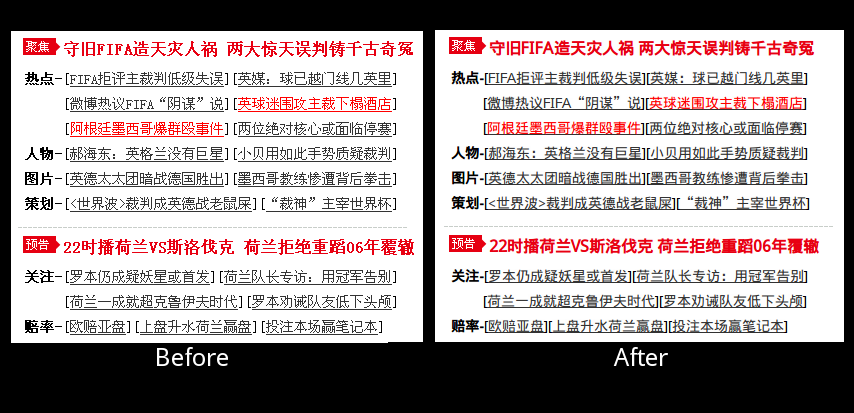
如果您在Windows 7或其他使用雅黑的系统下使用Chrome,也许会希望网页中文字体也统一使用雅黑来显示,然而国内许多网站直接指定了宋体作为页面字体,而Chrome自身又缺乏较好的字体偏好设置,使得有保留有宋体的Windows 7里Chrome会用不喜欢的点阵宋体来显示页面。
如果您希望在Chrome里干掉宋体,不妨试试用Force Microsoft Yahei Font扩展来强制让Chrome使用微软雅黑/文泉驿微米黑(而不是点阵宋体)显示网页。
缺点和其他浏览器强制字体一样,webfont 和定义了衬线体的网页会失效。